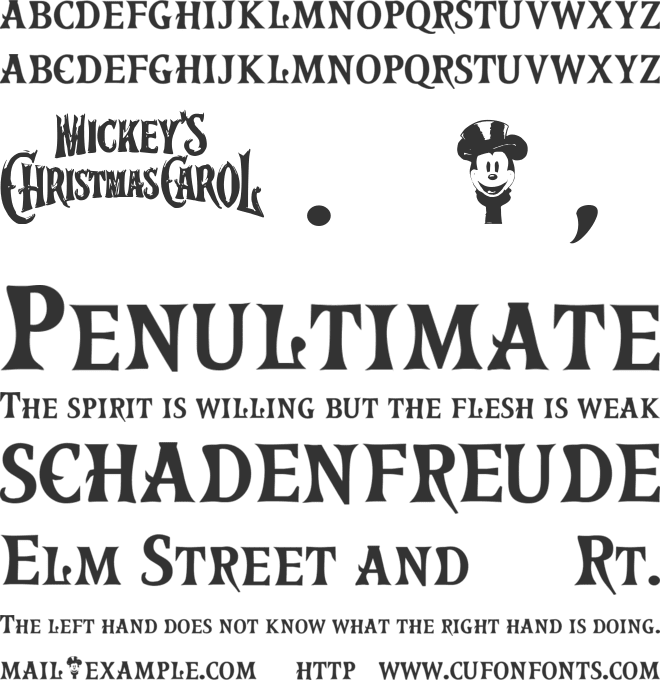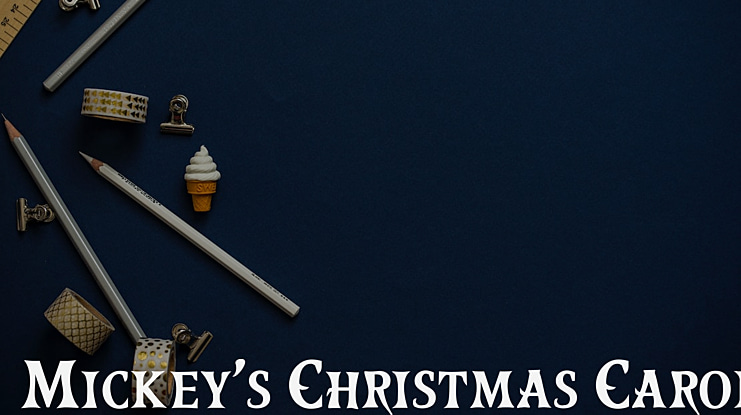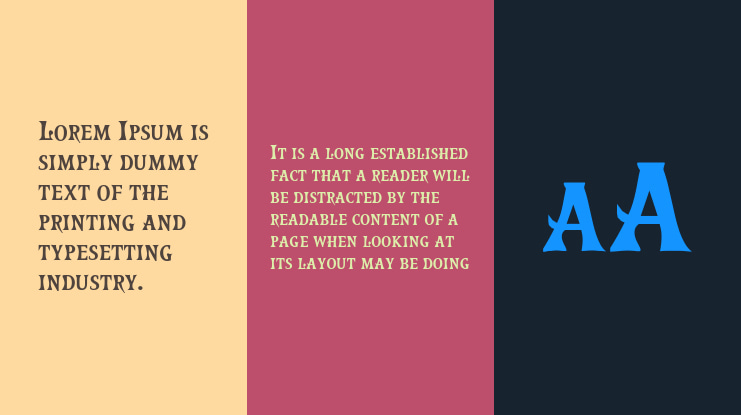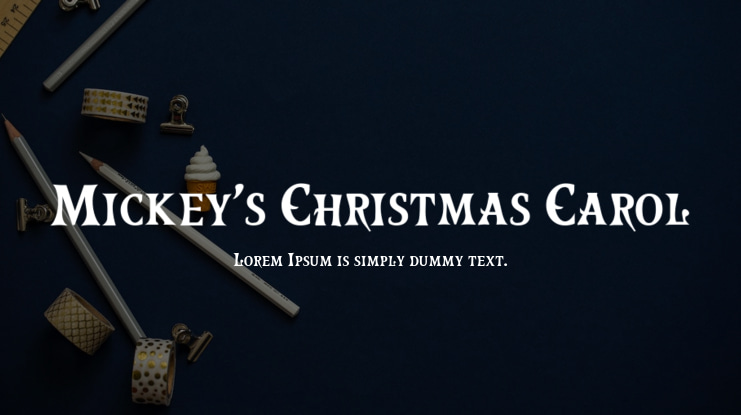
Mickey's Christmas Carol Font
Il magico Canto di Natale di Topolino in un font per deliziare le festività natalizie.
Mickey's magical Christmas Carol in a font to delight the holiday season.